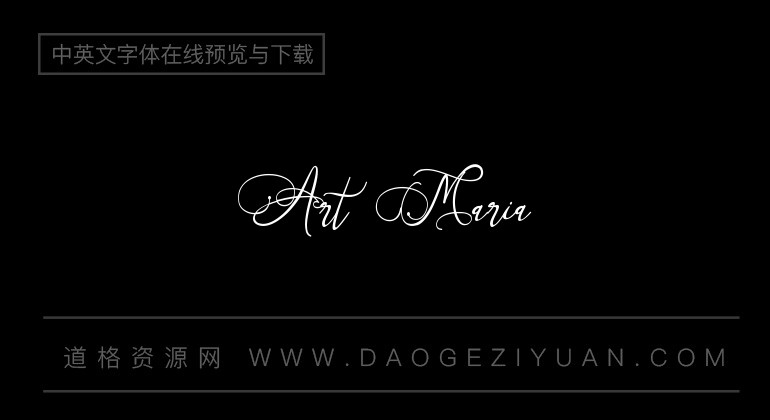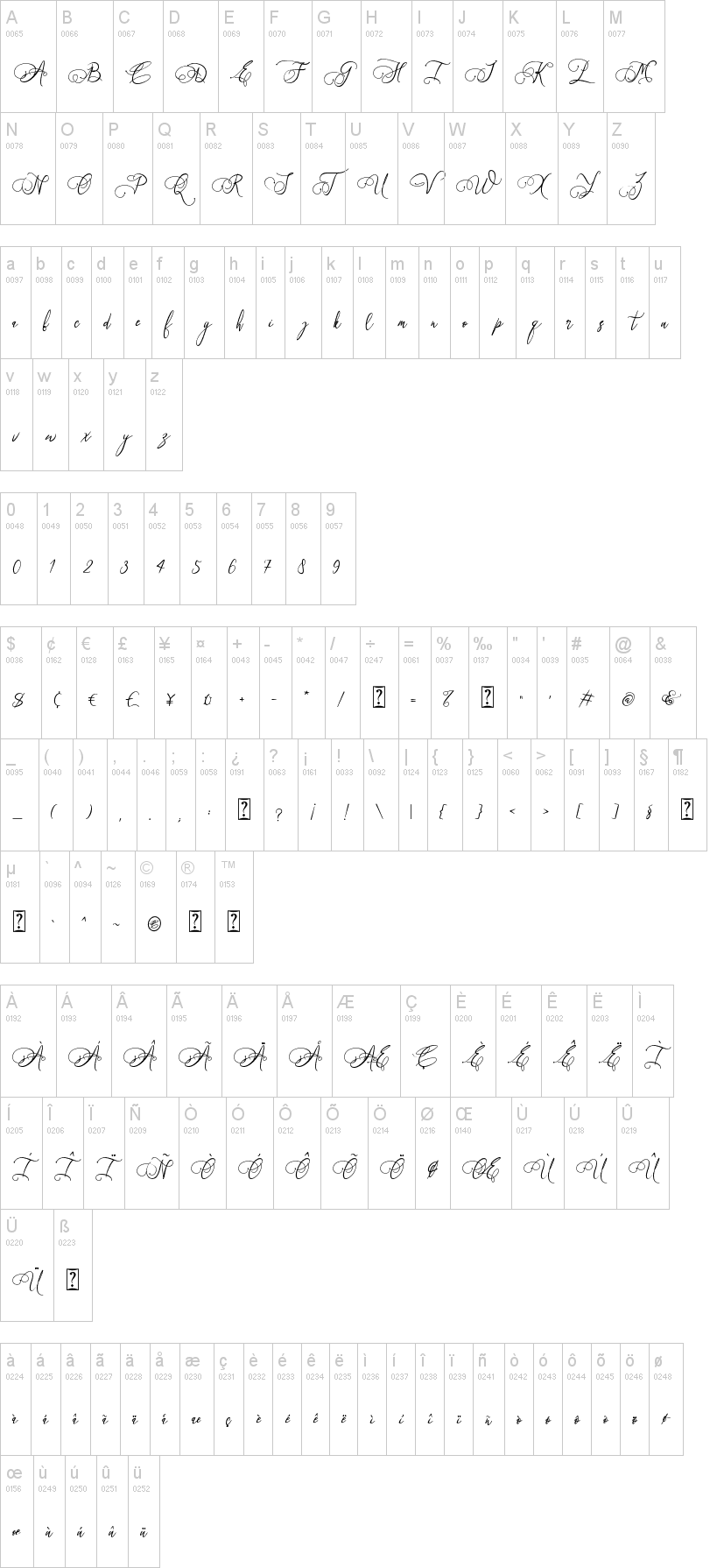
Art Maria
Art Maria是一款非常优雅的手写体字体,由著名的西班牙设计师Maria Ramos设计。它采用细节丰富的曲线和柔和的线条,使用一种流畅的笔触,表达出温暖、柔和的感觉。它可以用于创作艺术作品,也可以用于文字和标题,为您的设计增添更多的艺术性和灵动性。
Art Maria是一款非常不错的手写艺术字体,具有很好的视觉感,适合于文化类的宣传设计、商业类品牌的广告和产品包装设计以及个性化文字排版等较多场景。